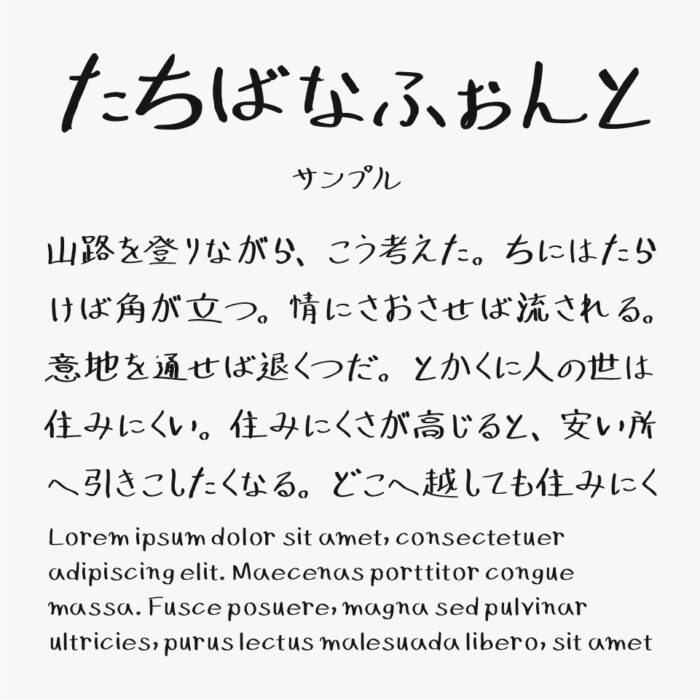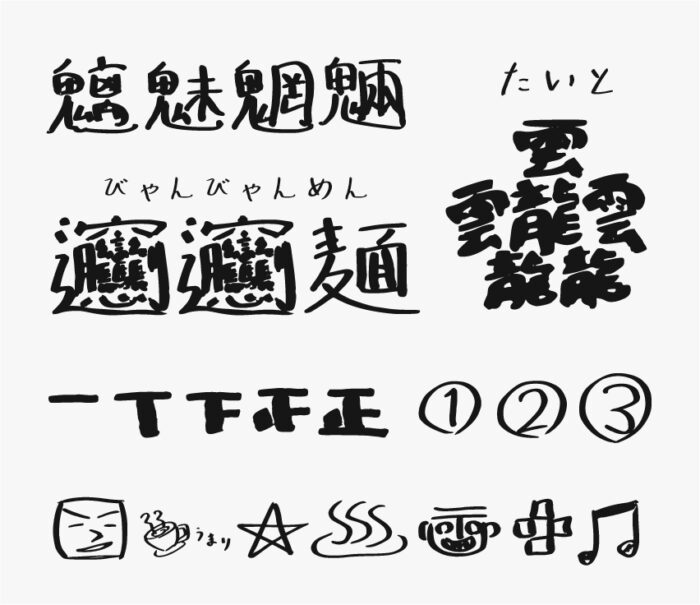
たちばなふぉんと(立花裕大さんの手書き文字)
たちばなふぉんと(たちばなフォント)は、俳優『立花裕大』さんによる手書きフォントです。
俳優さんによる手書き文字を、俳優さん自身で制作して配布しているフォントなので、とっても珍しくユニークな取り組みです。ファンの方には嬉しいプレゼントですね。
文字もとっても味わいがあり、可愛らしい文字なので、幅広いシーンで活躍できる手書き文字となっています。
「ビャンビャンメン」や「チミモウリョウ」など難しい漢字、絵文字や記号なども手書きで入っているのが面白いですね。
収録文字は、ひらがな・カタカナ・英数字・一部記号に加え常用漢字を収録しています。